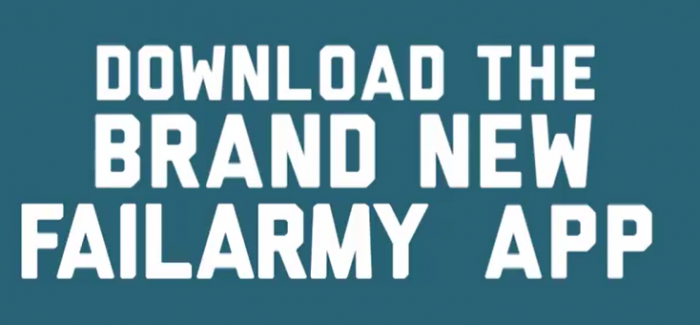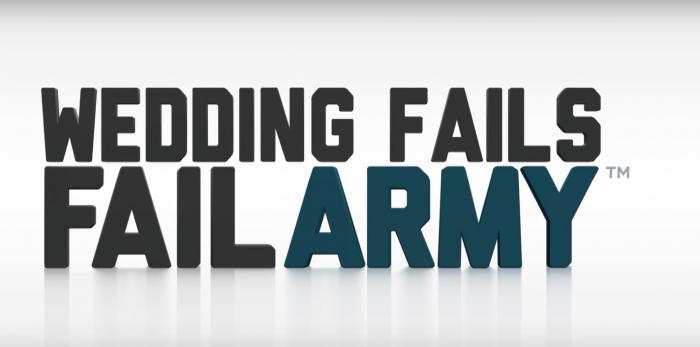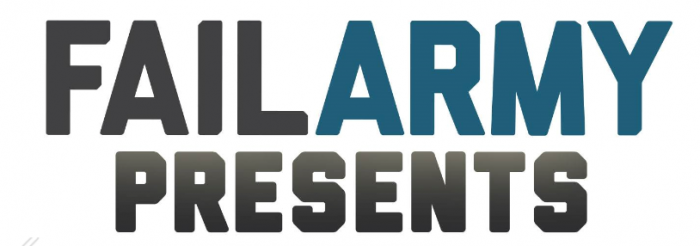
Welche Schriftart wurde auf den Bildern (Anhang) verwendet?
ich suche die Schriftart, die auf den Bildern im Anhang verwendet wurde. Danke! :)
Kennt vllt. jemand die genaue Schriftart, bei der alles gleich ist?
Gut möglich, dass es sich hier um immer wieder gern gemachte Markenzeichen-Buchstabenverstümmelung handelt. Also es die genaue Schrift so überhaupt nicht gibt, sondern der Gestalter der Marke zwar so eine typische Army-Schrift verwendet hat, aber daran im Illustrator herumgeschnippelt hat, um das Logo eigenständiger und nicht so einfach nachsetzbar zu machen.
Dass das so ist, sieht man ja an den Buchstaben bei "Wedding Fails", die die ursprüngliche Form wiedergeben.